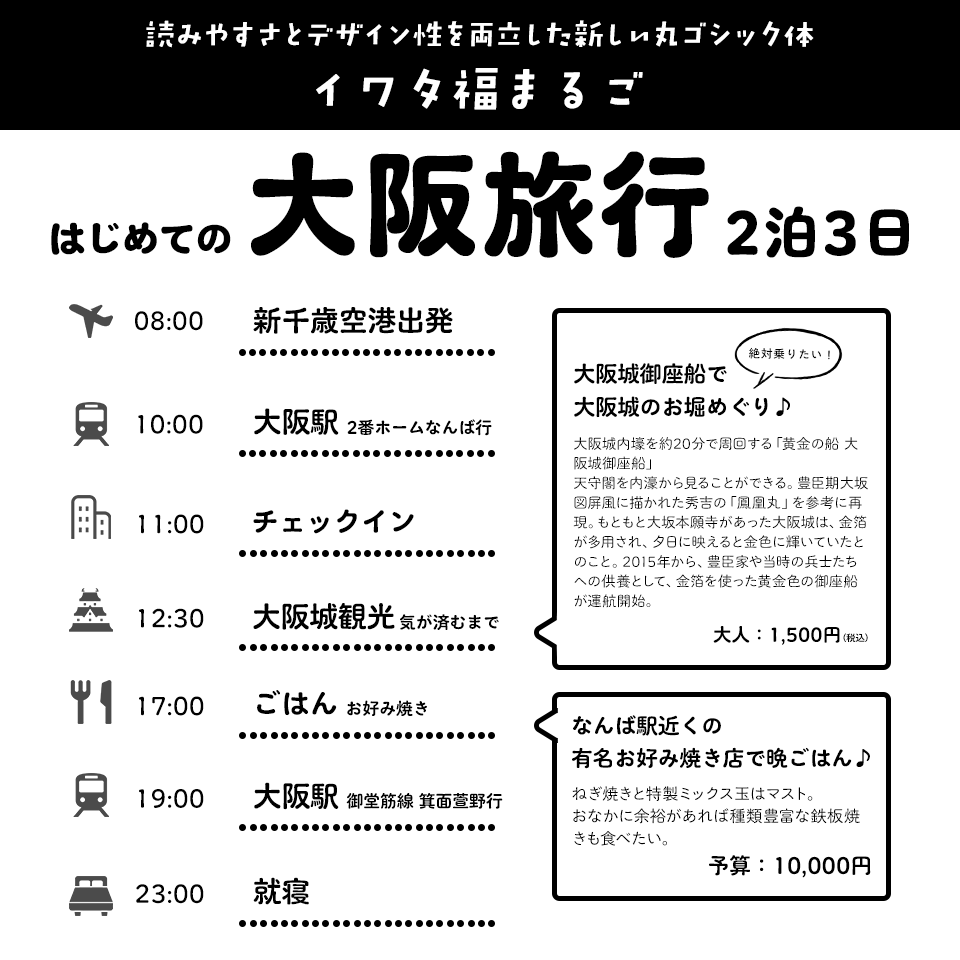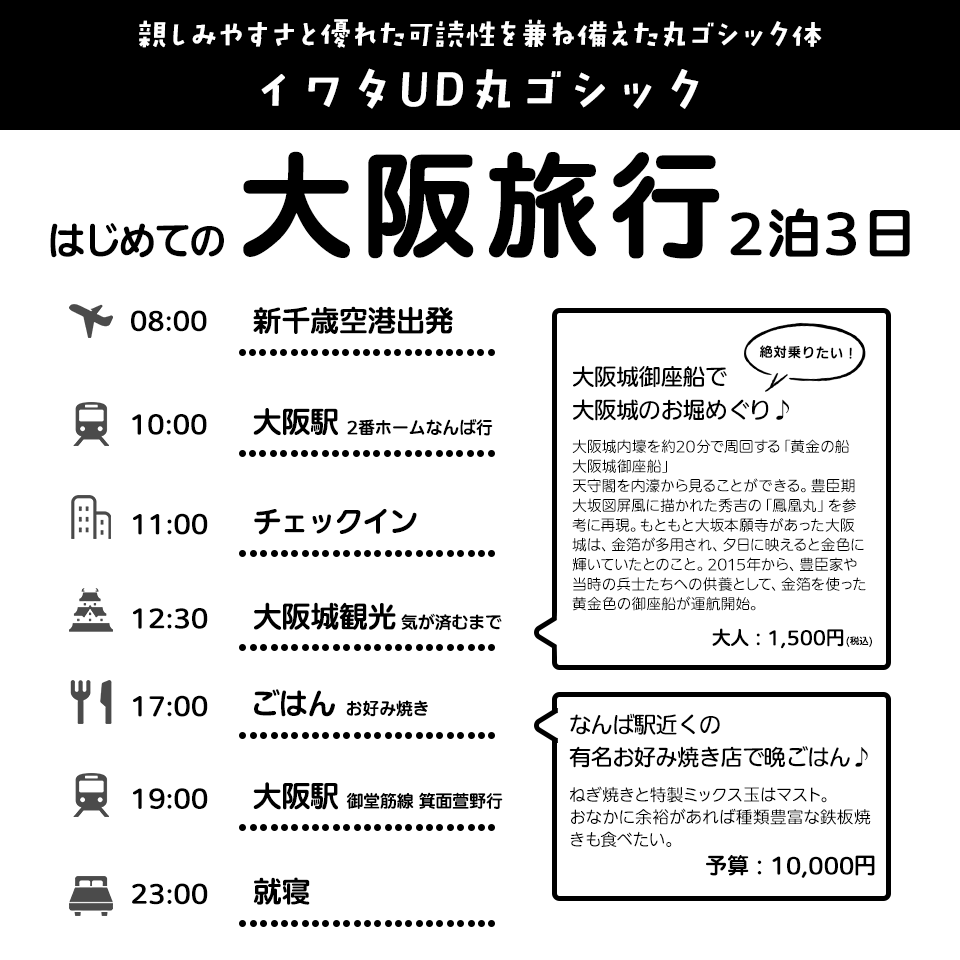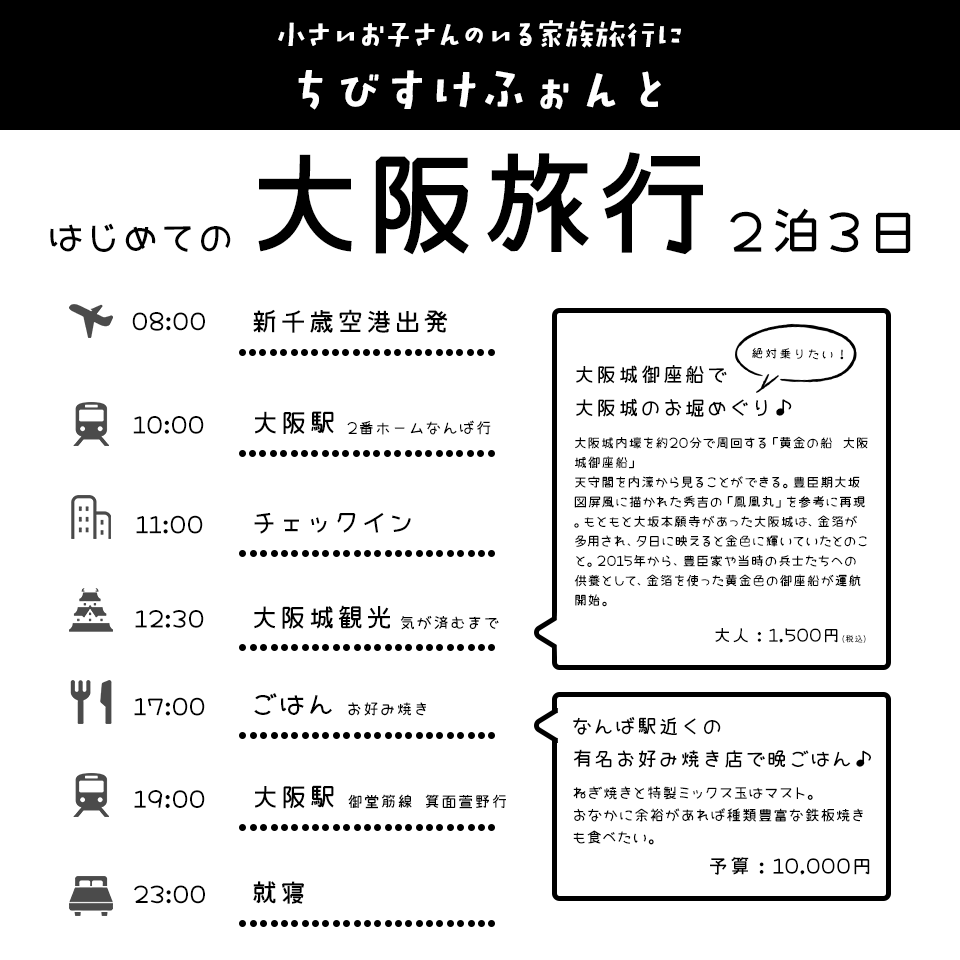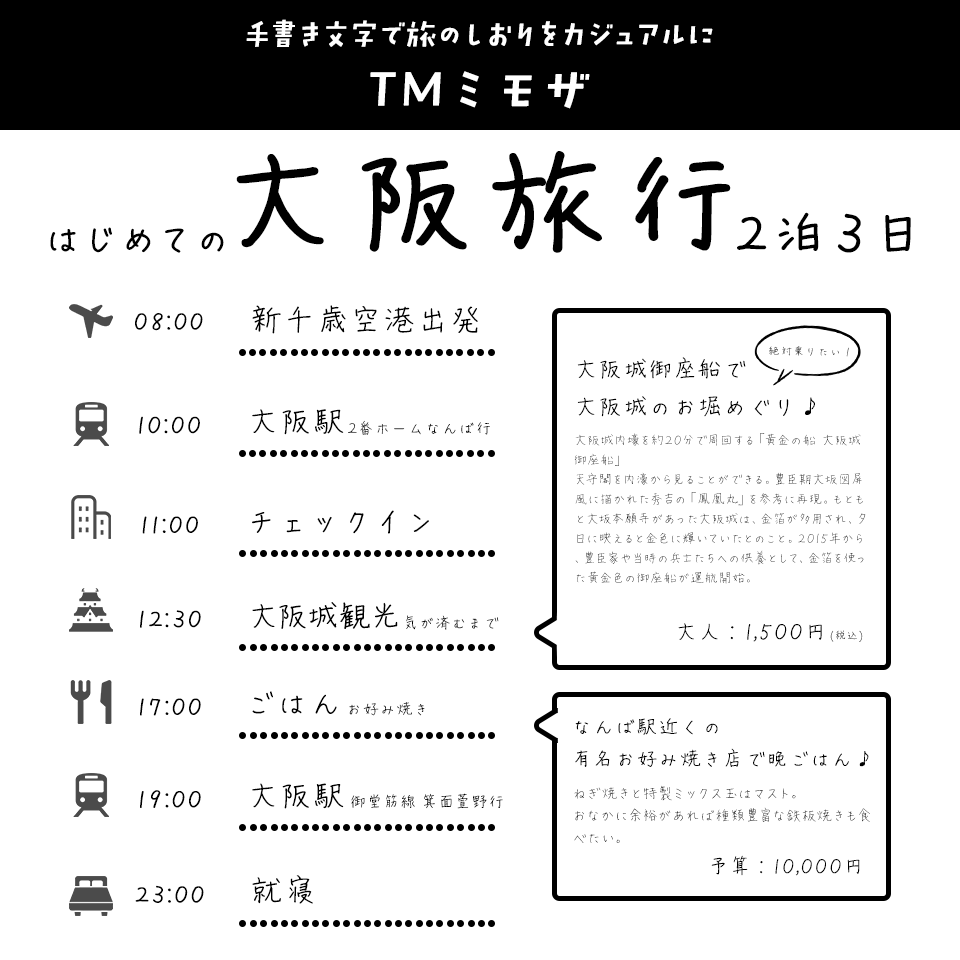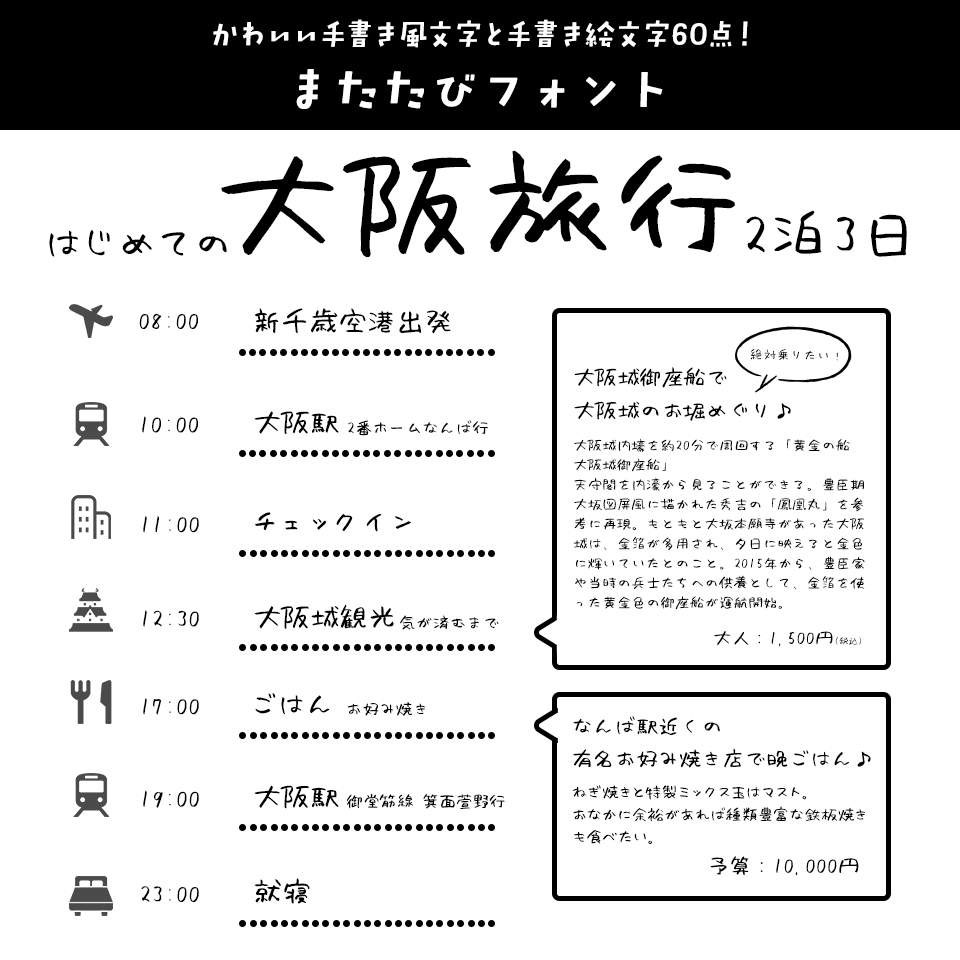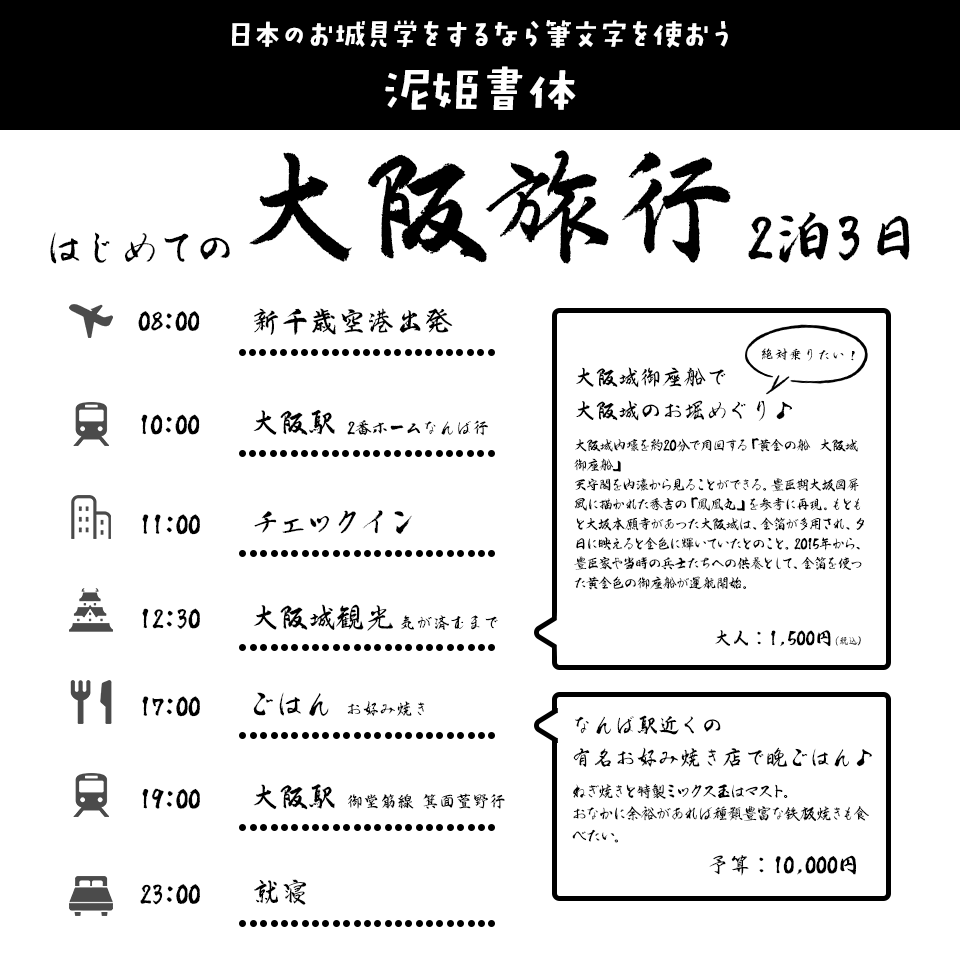
「旅のしおり」に合うフォント:特化型 目的別フォントガイド #145
今回は「旅のしおり」に合うフォント。日々フォントのことばかり考えている当店スタッフが直感的に選んだフォントをご紹介します。
「旅のしおり」に合うフォントをスタッフが選びました
「旅のしおり」に合うフォント イワタ福まるご
読みやすさとデザイン性を両立した新しい丸ゴシック体
イワタ福まるご【イワタ書体ライブラリー】
「旅のしおり」に合うフォント イワタ福まるご
有機的な曲線で構成されたこれまでにないシルエットの丸ゴシック体。ノーマルな丸ゴシックでは物足りないが、ポップ書体では強すぎる、そんなときの新しい選択肢になれる書体。見出しから文字組までしっかりこなせます。
「旅のしおり」に合うフォント イワタUD丸ゴシック
親しみやすさと優れた可読性を兼ね備えた丸ゴシック体
イワタUD丸ゴシック【イワタ書体ライブラリー】
「旅のしおり」に合うフォント イワタUD丸ゴシック
多くの人に分かりやすく、読みやすいように工夫されたUDフォント(ユニバーサルデザインフォント)の丸ゴシック書体です。やさしく、親しみやすい印象を与えることができるので、見出し・本文・補足など、どんな場面でも活躍してくれるフォントです
「旅のしおり」に合うフォント KOほくと武英M
大人の旅行にはきれいめ明朝体を
KOほくと武英M【欣喜堂】
「旅のしおり」に合うフォント KOほくと武英M
『新考北海道史』(奥山亮著、北方書院、1950)の本文書体から復刻した和字ニュースタイルの書体「ほくと」に、中国・清代の康熙帝・雍正帝の時代に銅活字を用いて作られた『古今図書集成』(1726)から復刻した過渡期明朝体「武英」、18世紀にイギリスのジョン・バスカーヴィル(1706~ 1775)が製作した活字が用いられている『田園詩と農事詩』(1757)から復刻したトランジショナルローマン体「K.E.Cancer Medium」を組み合わせた日本語書体です。
「旅のしおり」に合うフォント GSNPプリティフランクHS
懐かしい修学旅行のしおりによくある縁取り文字
GSNPプリティフランクHS【システムグラフィ】
「旅のしおり」に合うフォント GSNPプリティフランクHS
白抜きにシャドウの黒さが強い立体感を出していて、タイトルや見出しに使えるインパクトがある書体です。
「旅のしおり」に合うフォント ちびすけふぉんと
小さいお子さんのいる家族旅行に
ちびすけふぉんと【かに沢のりお】
「旅のしおり」に合うフォント ちびすけふぉんと
ちびちびした丸っこいかわいいフォントです。JIS第四水準までの漢字、人名用漢字など漢字だけでも約1万字を収録しています。こぶりかわいいフォントで家族旅行を盛り上げよう!
「旅のしおり」に合うフォント DSあかり
明るく軽やかな雰囲気のデザインフォント
DSあかり【七種泰史/デザインシグナル】
「旅のしおり」に合うフォント DSあかり
幅広い用途で大活躍間違いなしのフォント。どんなデザインに配置しても馴染む適度な太さがあり、角ばったフォルムとリズム感ある文字バランスが明るく軽やかな印象を与えます。
「旅のしおり」に合うフォント TMミモザ
手書き文字で旅のしおりをカジュアルに
TMミモザ【タンデムフォント】
「旅のしおり」に合うフォント TMミモザ
細めのペンのにじみを残した、自然で穏やかな手書き文字。癖は強すぎず、丁寧で読みやすいデザインです。
「旅のしおり」に合うフォント またたびフォント
かわいい手書き風文字と手書き絵文字60点!
またたびフォント【ゆるてがきこむ】
「旅のしおり」に合うフォント またたびフォント
よっぱらいのへろりとした文字が手書き感満載のフォント。おまけ素材の手書きPNG素材60点(png)も同梱しています。
「旅のしおり」に合うフォント ミウラ見出しLinerOtf R
温かみのある楽しさと質感が融合した手書き風フォント
ミウラ見出しLinerOtf R【ミウラフォント/モップスタジオ】
「旅のしおり」に合うフォント ミウラ見出しLinerOtf R
クレヨンみたいなザラっとした質感と、「ぐちゃっ」とした書き直し筆跡が特徴の「ミウラ見出しLinerOtf R」。手書き文字らしさを生かすために全ての文字を可変幅(プロポーショナル)で作成した特殊なフォントで、見出しやワンポイントに使ってみてください!
「旅のしおり」に合うフォント 泥姫書体
日本のお城見学をするなら筆文字を使おう
泥姫書体【昭和書体/コーエーサインワークス】
「旅のしおり」に合うフォント 泥姫書体
女流書家・恵彩院花梢による高解像度書体・第二弾。しっかりとした筆致にかすれのある、筆ならではの美しさと力強さを演出します。